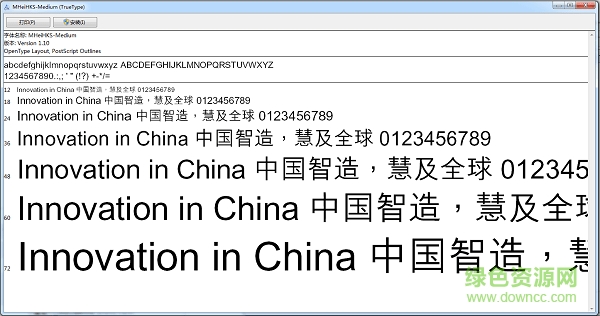
蒙納簡(jiǎn)中黑,字體安裝好后在字體欄里顯示的名稱(chēng)為:MHeiHKS-Medium,在簡(jiǎn)體系統(tǒng)里不顯示中文名稱(chēng)。蒙納字體為臺(tái)港澳地區(qū)使用的大五碼(BIG5)字體,所以在使用時(shí)不管這字體是簡(jiǎn)體還是繁體的,都必須直接輸入繁體字(如極點(diǎn)五筆輸入法就有這個(gè)功能)才能顯示所有文字,如果你輸入的是簡(jiǎn)體字,有的字就顯示為空白了。